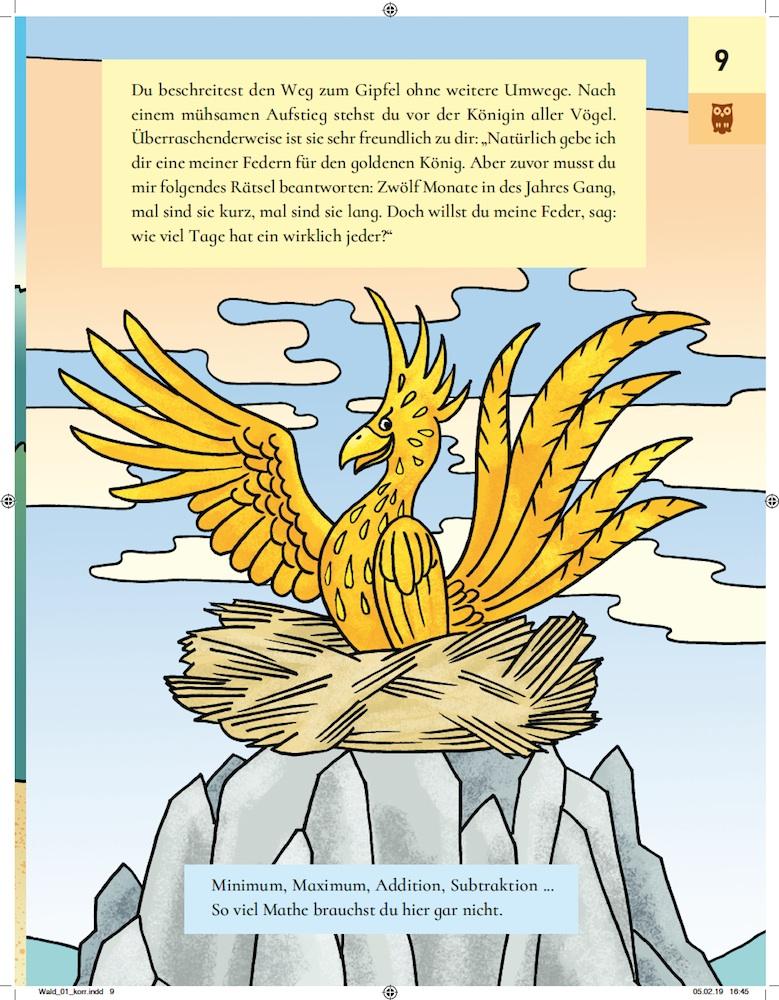
OpenType-Features in EB Garamond
Die OFL-lizensierte EB Garamond wurde über die ursprünglichen Arbeiten von Georg Duffner hinaus (http://www.georgduffner.at/ebgaramond/) durch Octavio Pardo erweitert (https://github.com/octaviopardo/EBGaramond12).
Duffner hatte zwei Schriftgrößen (12  und 8) als Regular, Italic und SC digitalisert (diese Fassung ist noch hier zu finden, https://www.fontsquirrel.com/fonts/eb-garamond), Pardo hat auf der 12er-Variante aufgebaut und unter anderem verschiedene Gewichte hinzugefügt. Die EB Garamond 08 von Duffner lässt sich für kleine Größen immer noch vorteilhaft mit der neuen EB Garamond kombinieren.
Die Opentype-Features der Duffner-Version sind gut dokumentiert, https://github.com/georgd/EB-Garamond/blob/master/specimen/Specimen.pdf?raw=true, die der Pardo-Version stimmen aber, wie ich feststellen musste,  nicht damit überein und sind nach meinem Kenntnisstand auch nicht dokumentiert :-(
Die Schrift gefällt mir sehr gut, Erik Spiekermann und ich haben insofern den gleichen Geschmack ;-)
Ich benutze keine Profi-Software, sondern LibreOffice, das ja seit geraumer Zeit Unterstützung für Opentype-Features anbietet.
Zur Anwendung dieser Schrift habe ich zwei Fragen, zu denen ich um Hilfe bitte:
Mit meinen beschränkten nicht-Profi-Werkzeugen fällt es mir schwer, die Opentype-Features herauszubekommen. Das eine oder andere habe ich durch Probieren gefunden. Mit otfinfo kann ich zwar eine Liste abfragen (am Ende des Beitrags ist sie angehängt), aber abgesehen von den selbsterklärenden weiß ich nicht, was ausgelöst wird. Gibt es einen anderen Weg, automatisiert abzufragen, was genau die Aktivierung der Features zur Folge hat? (So hat z.B. swsh nur Auswirkungen in der Kursiven, da konnte ich im Regular-Schnitt probieren, so lange ich wollte...)
Und die zweite Frage:
Zumindest bei den von mir genutzten Werkzeugen wird zwar bei fi, nicht aber bei , und eine Ligatur gesetzt. Das ist schon in der Regular bei unschön und bei und gerade noch erträglich, wenn es fetter wird, geht es gar nicht.  Es gibt vielleicht ja eine schmalere f-Variante, die idealerweise automatisch gesetzt werden sollte, die ich aber auch manuell nachpflegen kann - wie bekomme ich den Unicode dafür heraus, falls sie existiert? Oder existieren -, - und -Ligaturen, die nur nicht automatisch gesetzt werden?
Falls jemand Freude hat, den Dateien mit besserem Werkzeug auf den Leib zu rücken, wäre ich sehr dankbar. Bei dieser wirklich schönen Schrift wäre es schade, wenn das f-Problem nicht behoben werden kann.
So, zitternden Fingers habe ich jetzt FontForge installiert und den Font geöffnet. Zu den OpenType-Features bin ich noch nicht vorgedrungen, aber zu meiner zweiten Frage von oben habe ich herausgefunden, dass es tatsächlich ein short f gibt.
Ganz am Ende der Zeichentabelle wird es angezeigt, nur: Es hat den gleichen Unicode-Wert wie das Standard-f, nämlich 0066. Mein Plan, es manuell einzugeben bzw eine Ersetzung laufen zu lassen, kann also nicht aufgehen, da ich das Zeichen nicht erzeugen kann.
Ist diese Codierung mit gleichem Wert normal? Was kann ich tun, damit short f vor üöä angezeigt wird? Und vermutlich sind das ja nicht die einzigen sinnvollen Einsätze, vor schließenden Klammern, Abführungszeichen, Frage- und Ausrufezeichen wäre es auch besser...
Es hat den gleichen Unicode-Wert wie das Standard-f, nämlich 0066.
Nein, es hat gar keinen Unicode-Wert. Das ist für Alternativglyphen, die nur per Opentype angesprochen werden können/sollen, normal. (Es sieht nur so aus, als hätte es denselben Unicode-Wert wie das normale f. Fontforge weiß, dass f.short eine Version des f ist und zeigt das dann so komisch an.)
Was kann ich tun, damit short f vor üöä angezeigt wird?
Soweit ich sehen kann, lässt sich f.short zumindest in der Regular, die ich angekuckt habe, gar nicht ansprechen, auch nicht per Opentype. Da es eine OFL-Schrift ist, darfst du aber selbst Hand anlegen oder einen Forumsfreund darum bitten. Ideal wäre es vielleicht, das gleich mit Glyphs zu machen (die Source-Dateien stehen im Github), aber wenn sie da niemand findet, modifiziere ich dir gerne die TTF- oder OTF-Fonts mit Fontforge.
Toll! Für Kinderbücher?
Þorstelinchen liest mit Begeisterung National-Geographic-Kids-Bücher, die eine ähnliche Schrift verwenden. Funktioniert prima (übrigens auch mit dem zweistöckigen a).
Da sehe 🔍 ich aber nur einen Urheberrechtshinweis in einer Garamond. Haste mal ein Foto mit ein bisschen mehr Text?
Kommt da nix, wenn du die Look Inside / Blick ins Buch -Funktion benutzt?
Ansonsten gern auch dies: